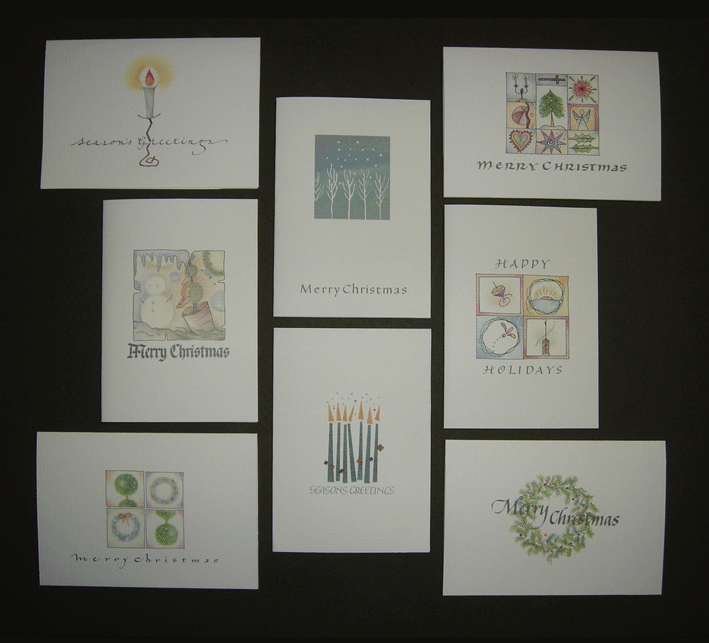
G・コレクションのカード
神戸のH子さんとmakikoさん、最強コンビのお二人のカードが完成です! 感動的にきれいです・・・・・ためいき。
以前もご紹介した阪急宝塚駅のG・コレクションのノベルティグッズです。こんなに素敵なカードのセットがノベルティグッズ!?? ・・・・という事は市販されていないってことなんですよ!? なんということでしょう・・・・販売の予定はないのでしょうかねぇ。
makikoさんの素敵なイラスト。見る度にますます洗練されてきて、個性的です。それを上手に生かすH子さんの美しくシンプルな文字。柔らかくて暖かいクリスマスの雰囲気を見事に表していますね。ああ、このカードの原画を見てみた〜〜い。カードの実際のサイズよりも大きく書いているのかしら。もしかして、文字とイラストは別々で制作しているのかもしれませんね。
このカードは8枚がセットなのだそうですよ。買えないならどこに行ったらもらえるのでしょうね。カリグラフィーもH子さんもmakikoさんも知らない人でも、こんなカードのセットを頂けたら、嬉しいでしょうねぇー・・・
ああ、羨ましい!